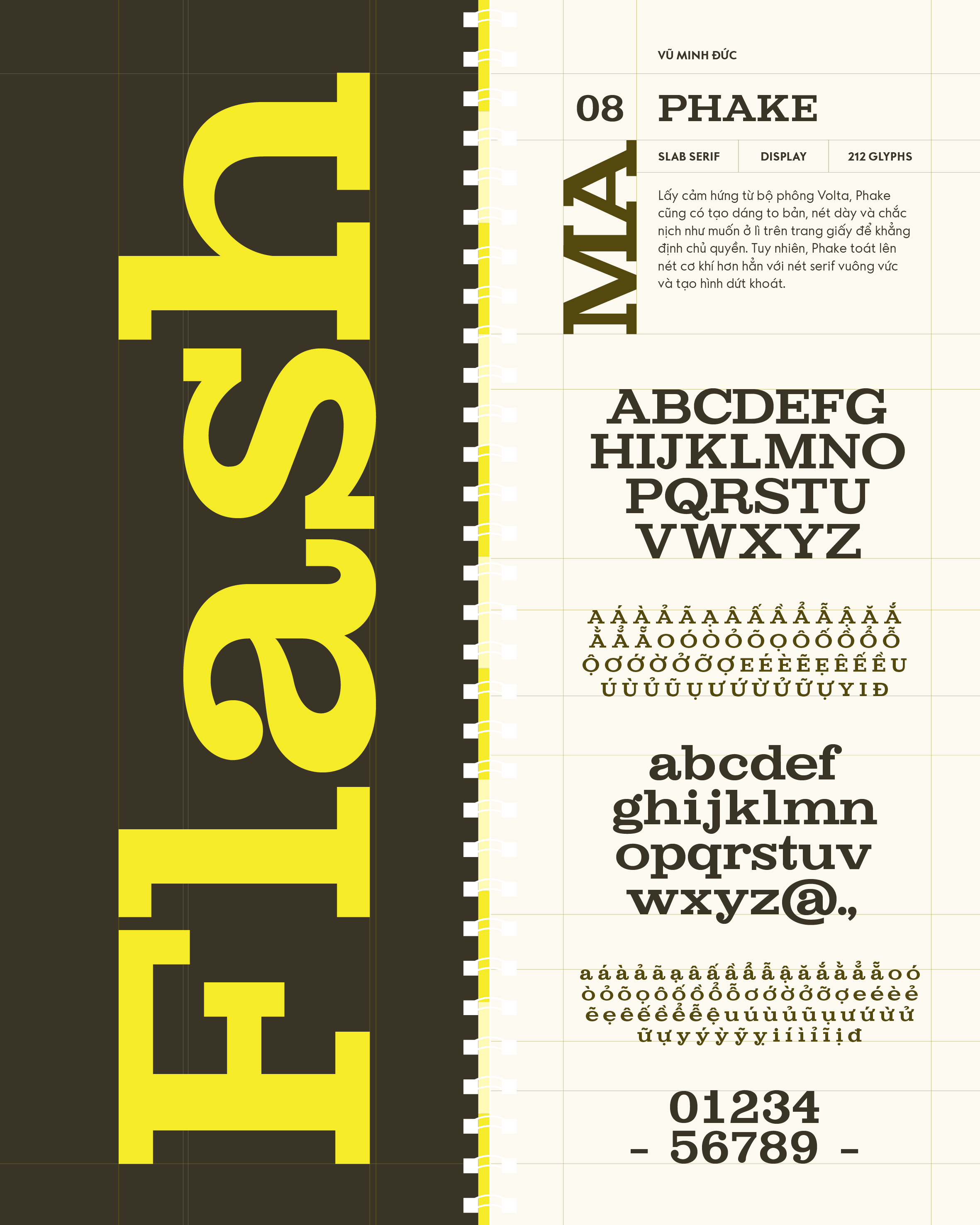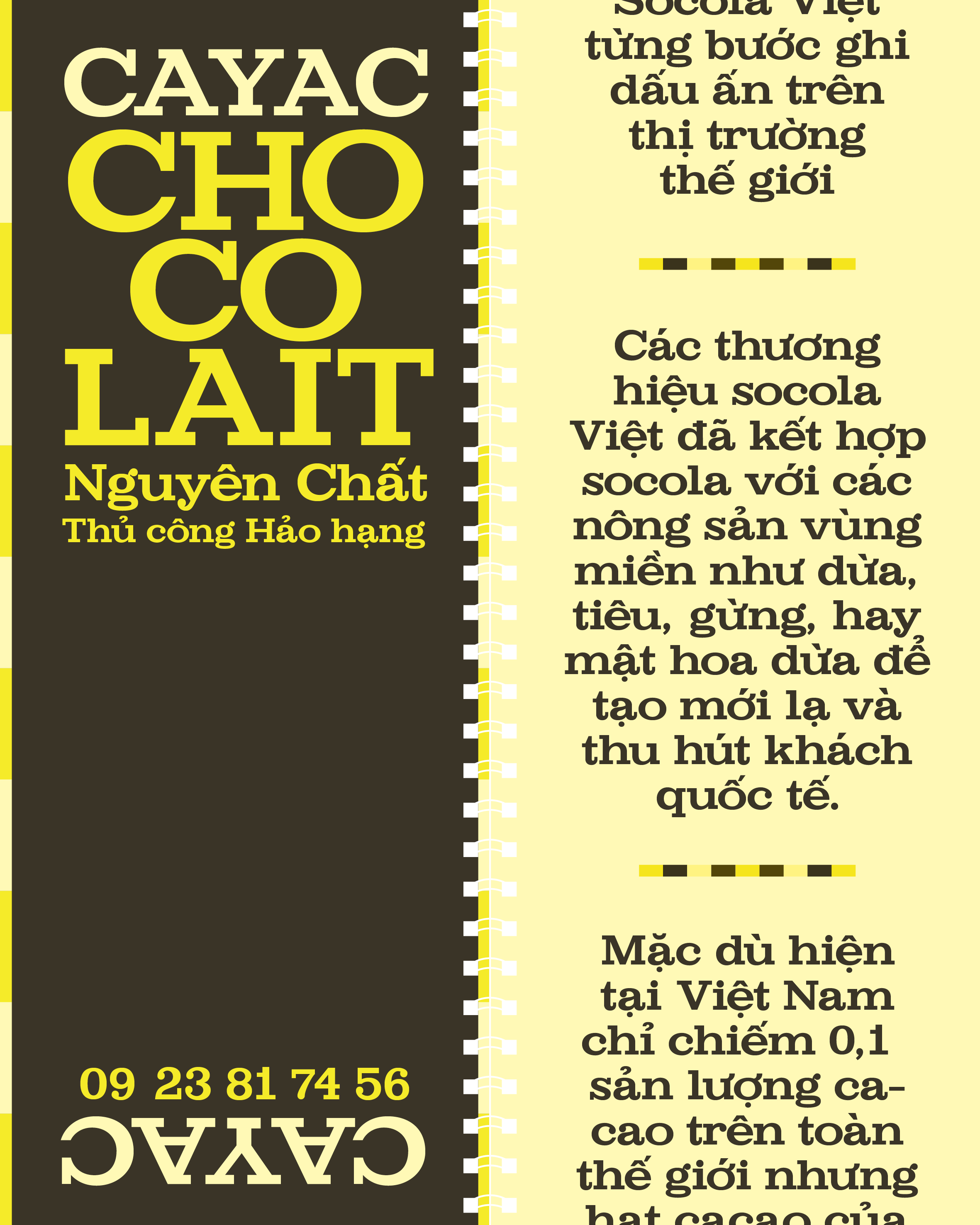
Phake
Về Phake: Lấy cảm hứng từ bộ phông Volta, Phake cũng có tạo dáng to bản, nét dày và chắc nịch như muốn ở lì trên trang giấy để khẳng định chủ quyền. Tuy nhiên, Phake toát lên nét cơ khí hơn hẳn với nét serif vuông vức và tạo hình dứt khoát.
Slab Serif
Display
Vũ Đức Minh